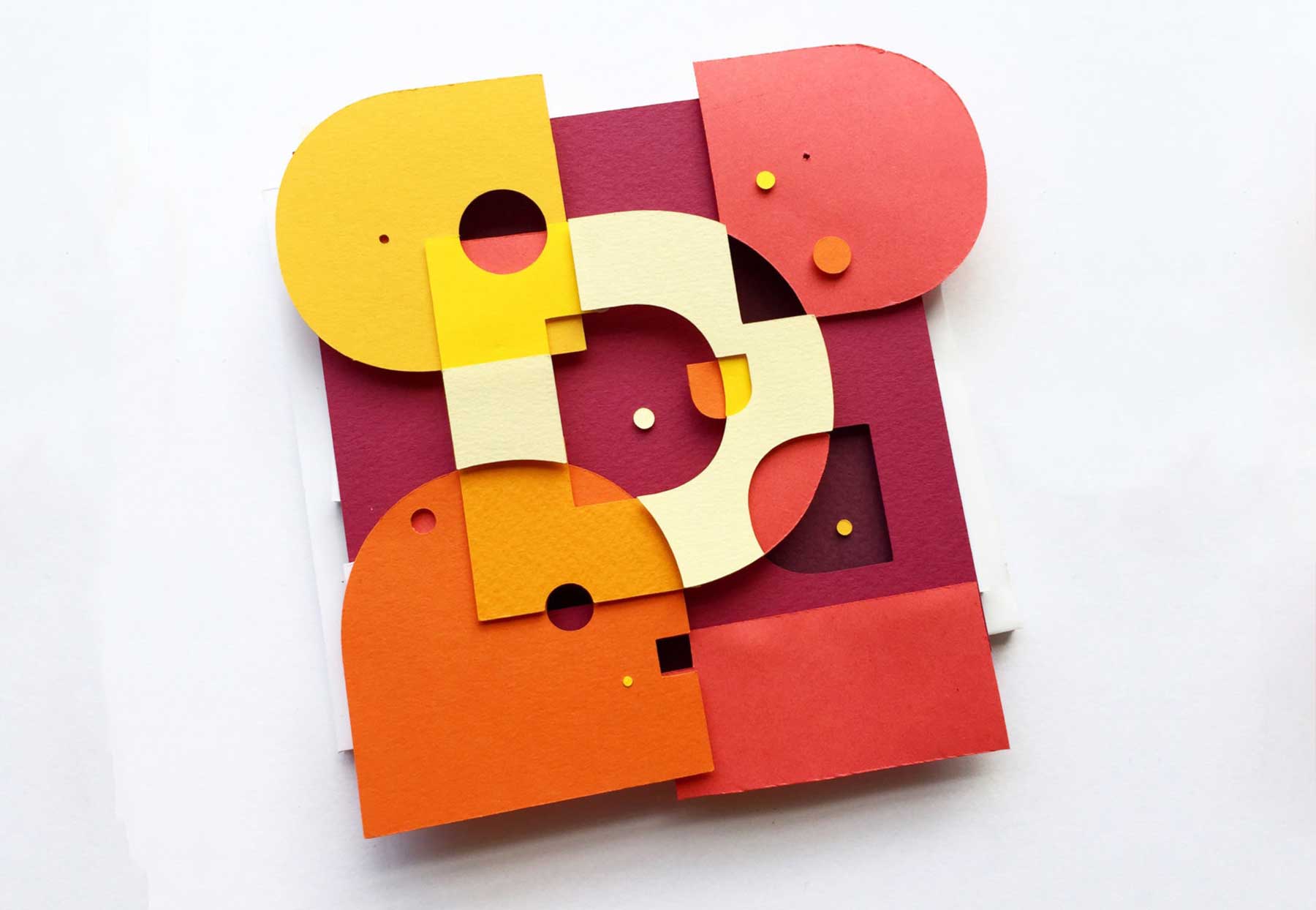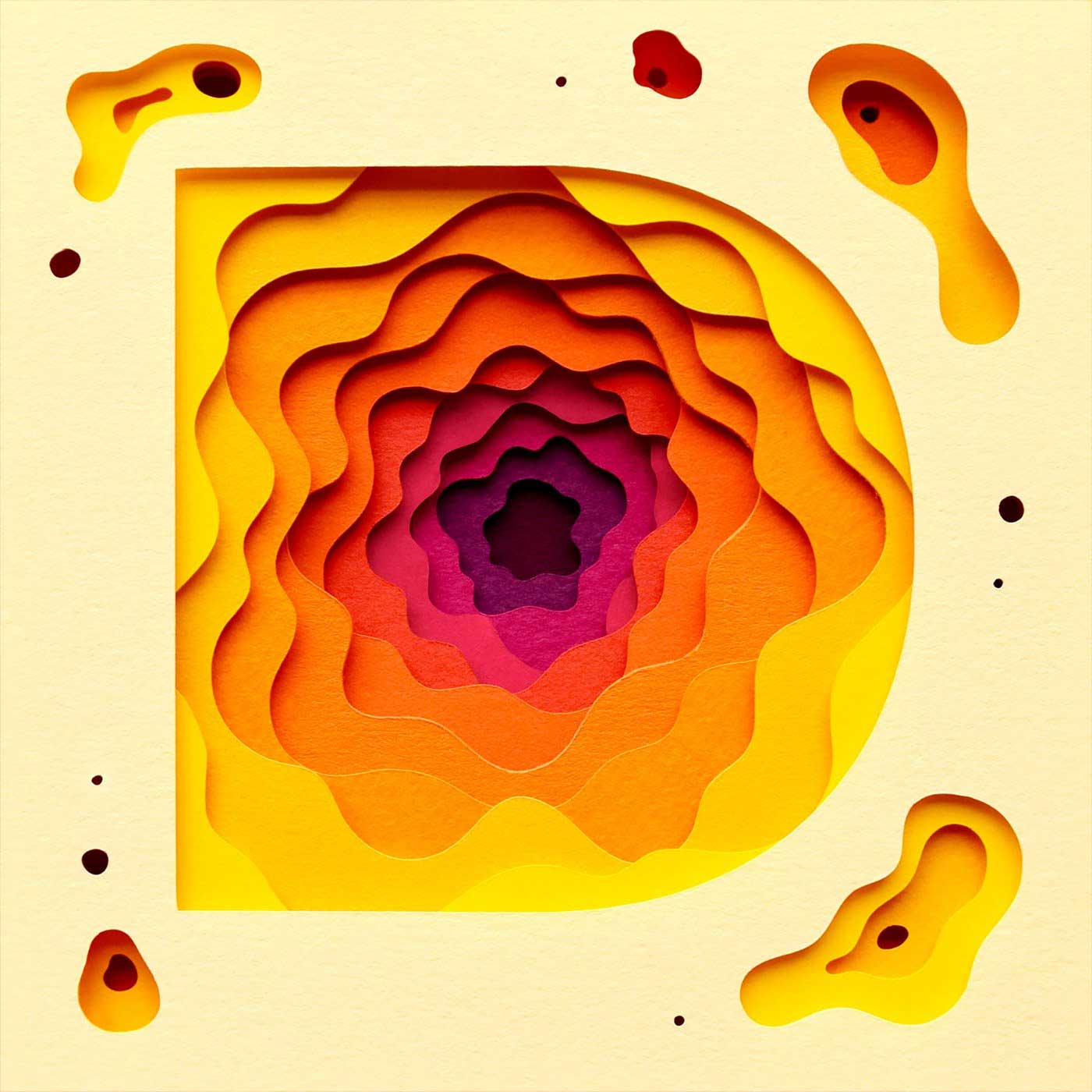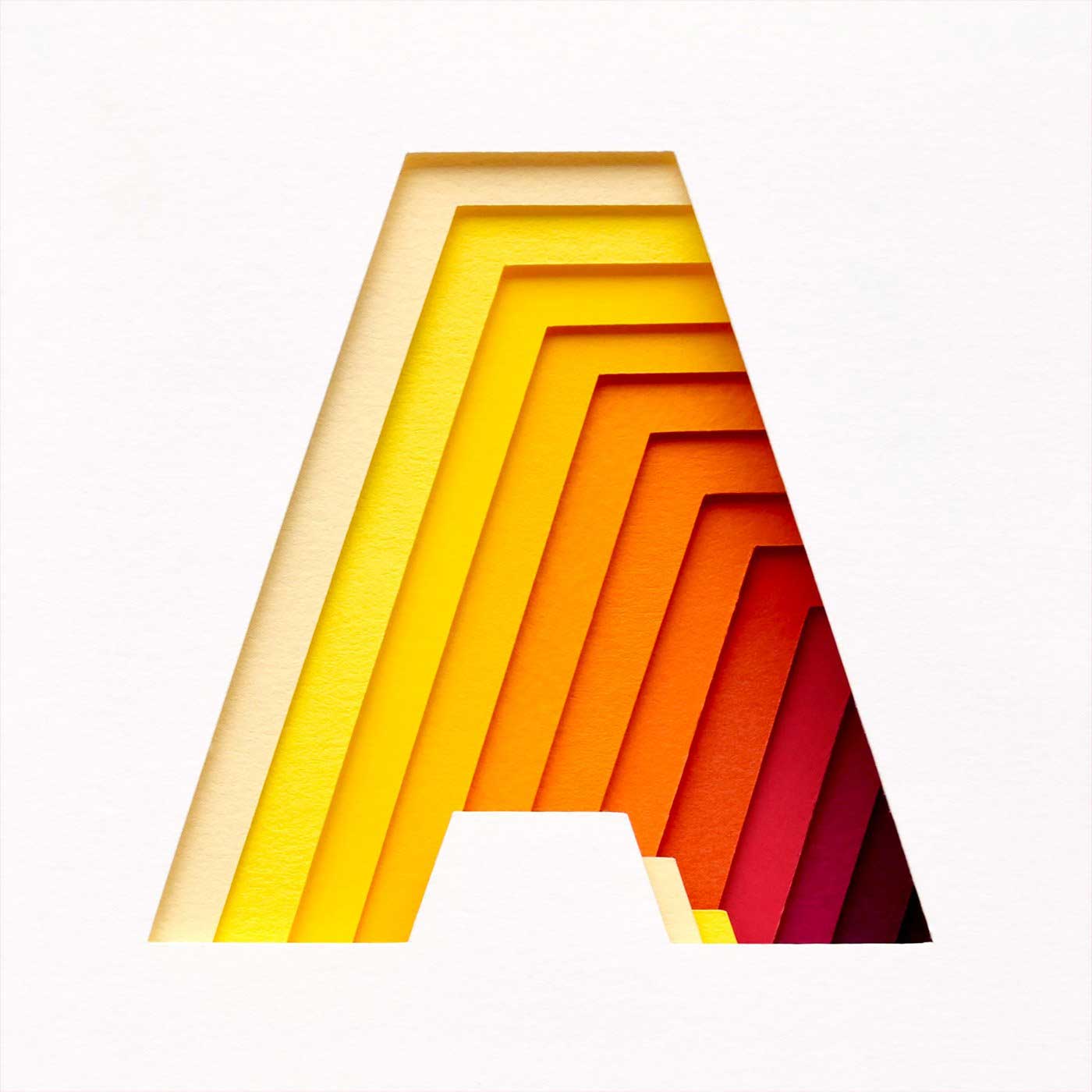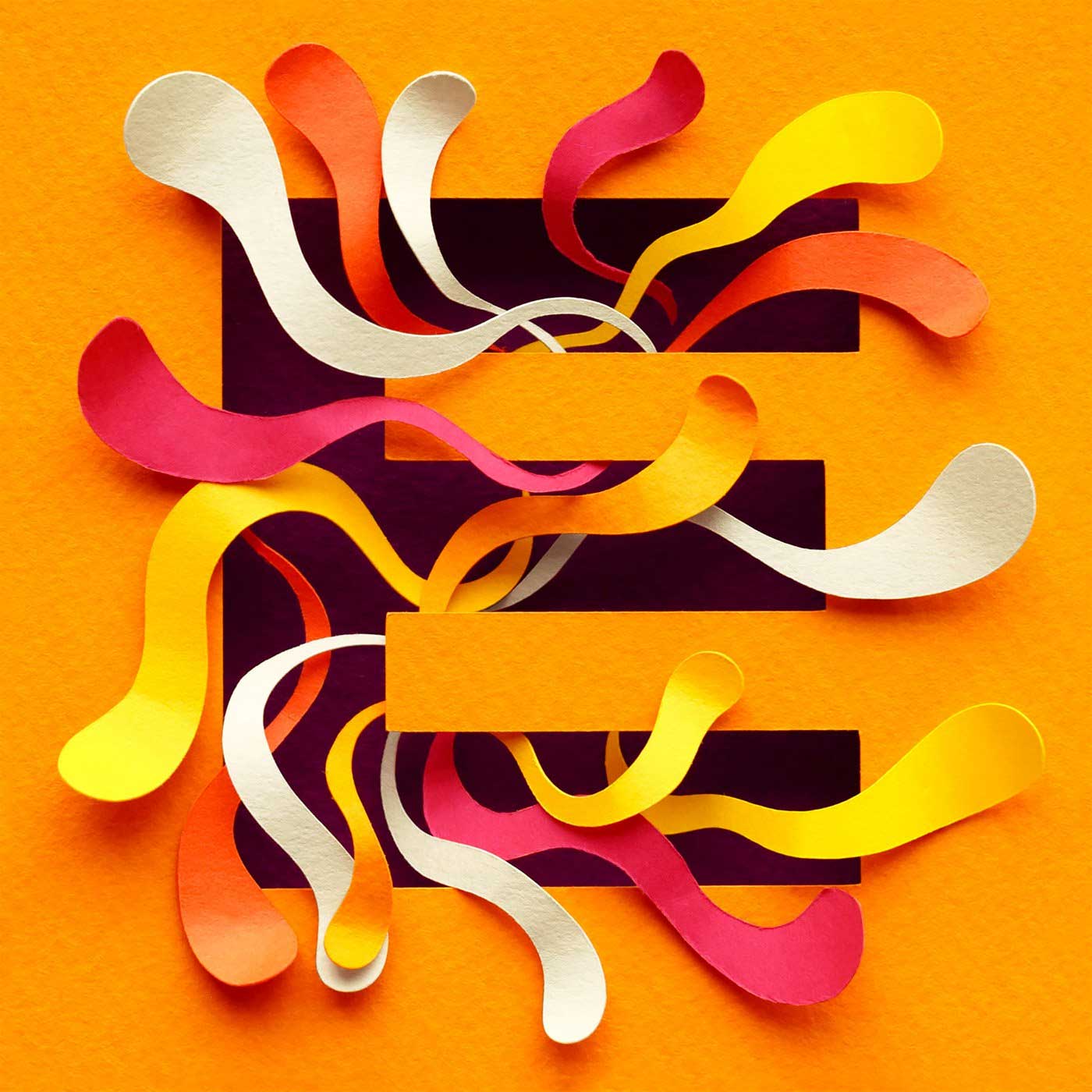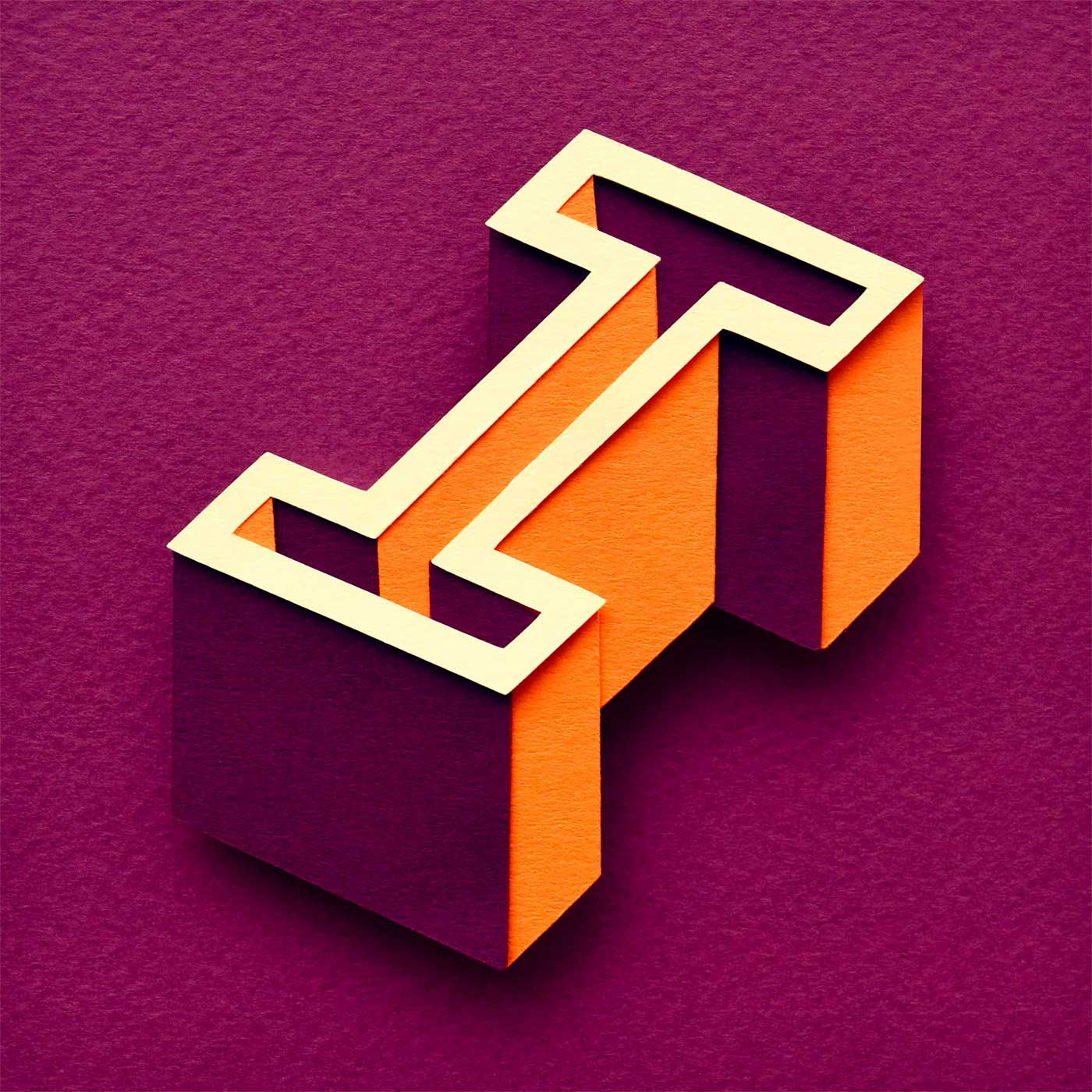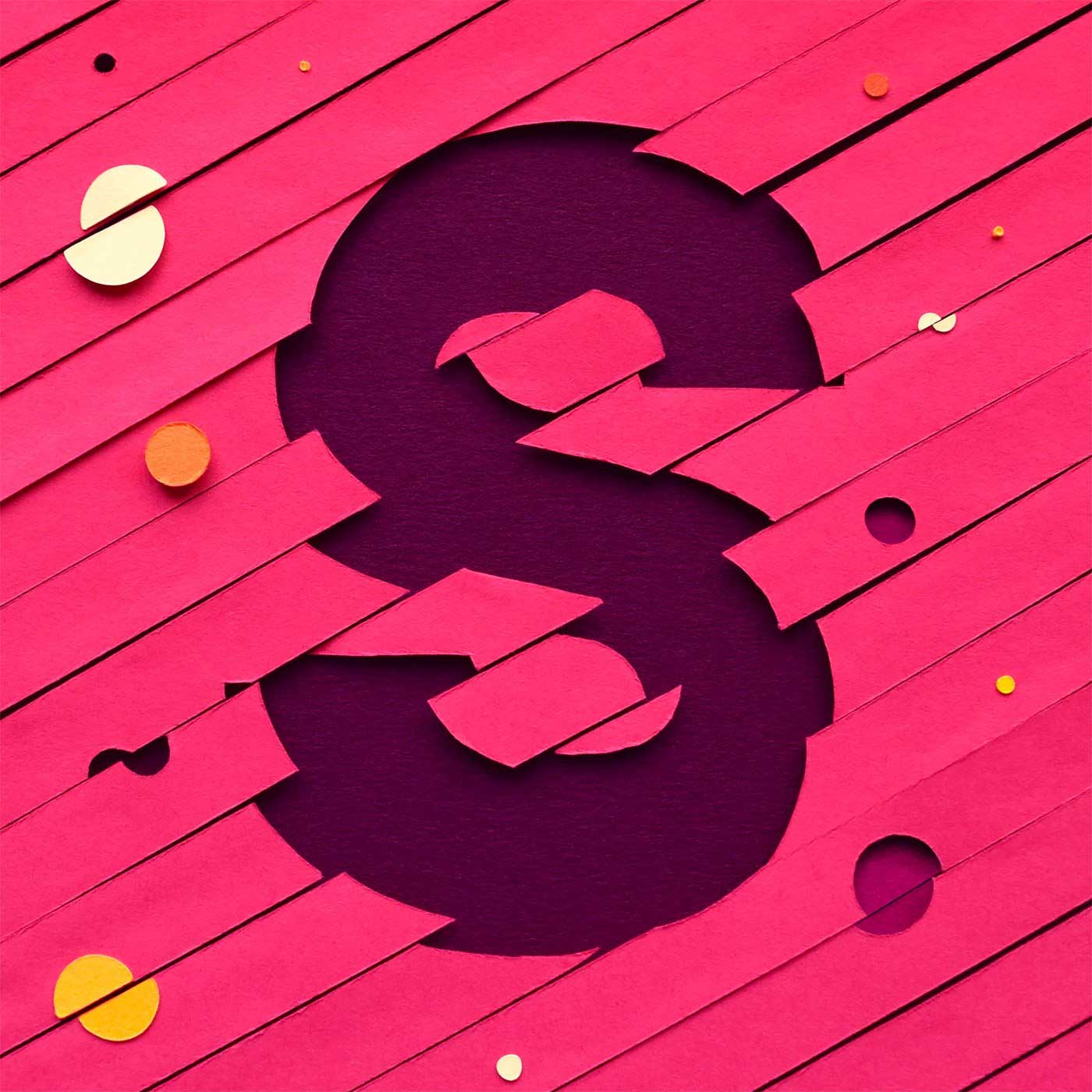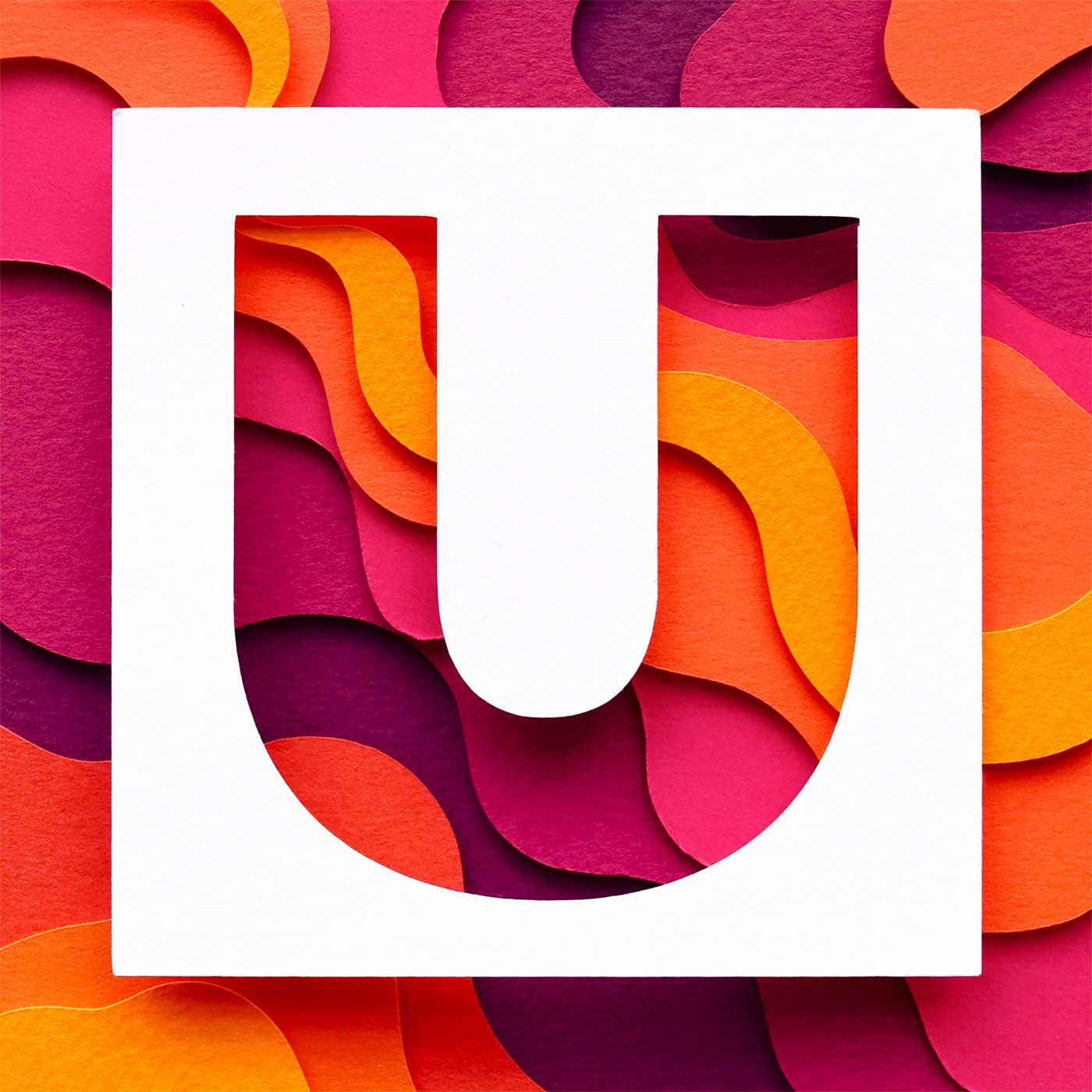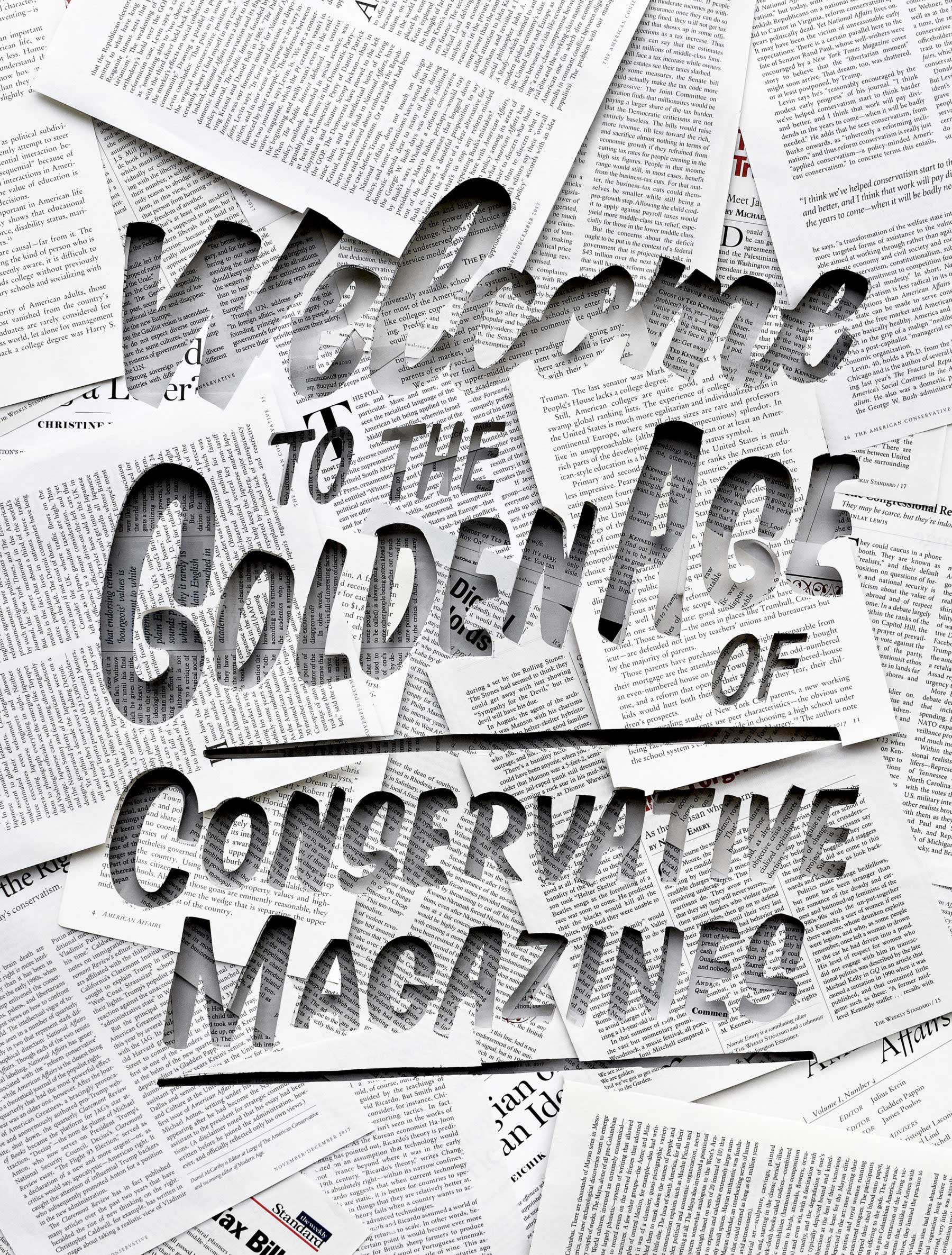
Neue Arbeiten von Owen Gildersleeve
Papier trifft Typografie
Vor sechseinhalb Jahren(!) hatte ich euch die kreativen Papierarbeiten von Owen Gildersleeve vorgestellt. Mittlerweile erstellt der Londoner neben detailverliebt zugeschnittenen Poster- und Covermotiven auch tolle Typografie-Arbeiten. Alles stets sehr sauber erarbeitet und farblich wie strukturell stimmig konzipiert – nicht umsonst hagelte es bereits etliche Auszeichnungen. Hier ein kleines Update.
„Owen’s work often plays with light and shadow, combining hand-cut layers of paper with graphical forms and hand-rendered typography. His creations range from small-scale intricate paper illustrations that he shoots at his studio in East London, to large-scale sets and installations, for which he often collaborates with other creatives to help bring his ideas into being.“ (Artist Statement)